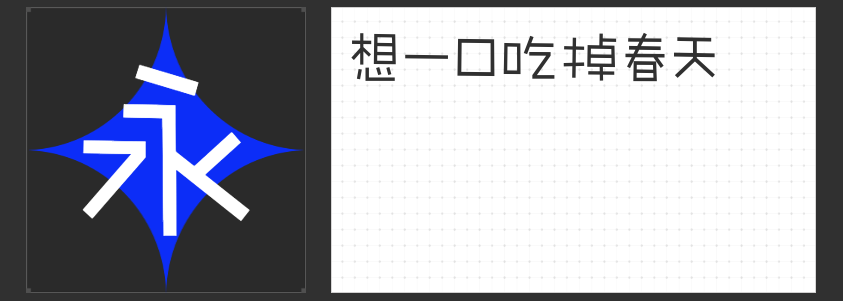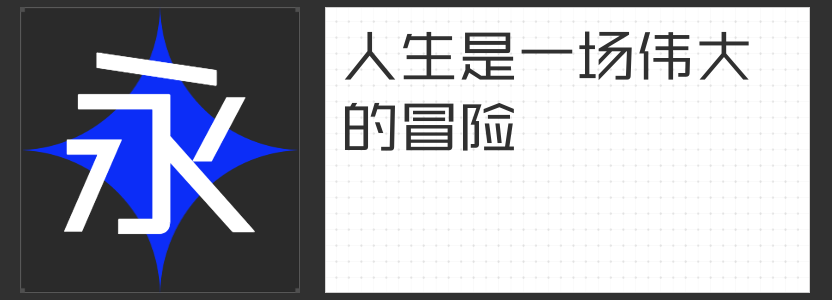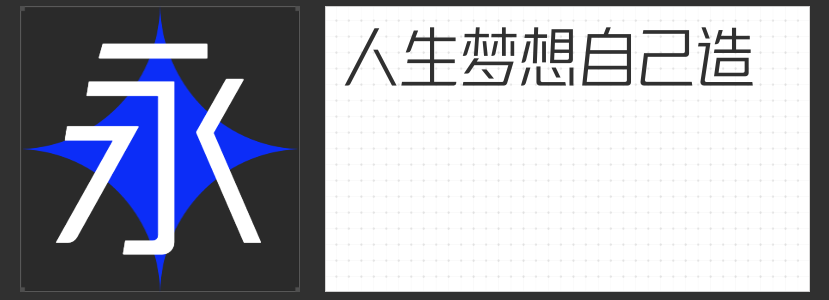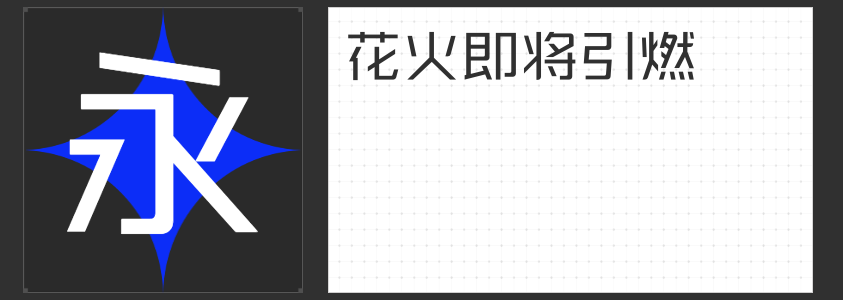
视频&字体共舞:四款精选字体,赋能创意无限
在数字设计的广阔舞台上,励字造梦,共创字库携手剪映,为视频创作者们带来了四款风格迥异却又同样出色的字体。这些字体不仅在设计上独具匠心,更在视频编辑中展现出非凡的适应性,为作品增添无限魅力。
1.励字勇敢黑简 常规
设计用途:适合打造具有冲击力和力量感的视频标题、字幕或宣传语。无论是电影预告、体育赛事还是励志演讲,其粗犷而坚定的线条都能完美传达出勇往直前、不屈不挠的精神风貌。
优点:提供多样化的字重选择及可变字体功能,让创作者能够根据视频的情感氛围和视觉效果进行微调,实现字体与内容的无缝融合。
2.励字敲可爱简 常规
设计用途:专为轻松愉悦、温馨可爱的视频内容设计,如Vlog分享、儿童教育、宠物日常等。其圆润可爱的字形能够迅速拉近与观众的距离,营造温馨和谐的观看体验。
优点:多变的字重搭配可变字体特性,让创作者能够轻松打造个性化十足的可爱风格,让视频内容更加生动有趣。
3.励字志向黑简 常规
设计用途:适用于激励人心、表达个人志向或企业愿景的视频内容。无论是励志演讲、创业故事还是人生感悟,其沉稳而富有激情的字体风格都能有效激发观众的共鸣和思考。
优点:通过精细的字重控制和可变字体技术,创作者能够精准把握字体表达的情感力度,使视频信息传达更加精准有力。
4.励字造梦简 常规
设计用途:作为通用性极强的字体,适用于各种风格和主题的视频创作。无论是科技、时尚、艺术还是日常生活,其简洁而富有想象力的设计风格都能为视频增添一抹独特的韵味。
优点:丰富的字重选项和可变字体功能为创作者提供了极大的自由度,让视频设计不再受限于单一风格,而是能够随心所欲地探索和创造。
总之,与剪映合作的这四款字体,不仅在设计上各具特色,更在视频编辑中展现出了强大的适应性和表现力。它们不仅是创作者们手中的得力工具,更是推动视频内容创新和提升视觉品质的重要力量。